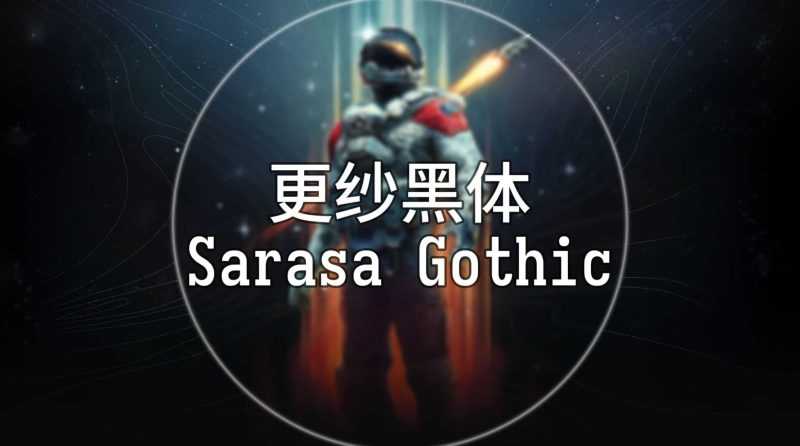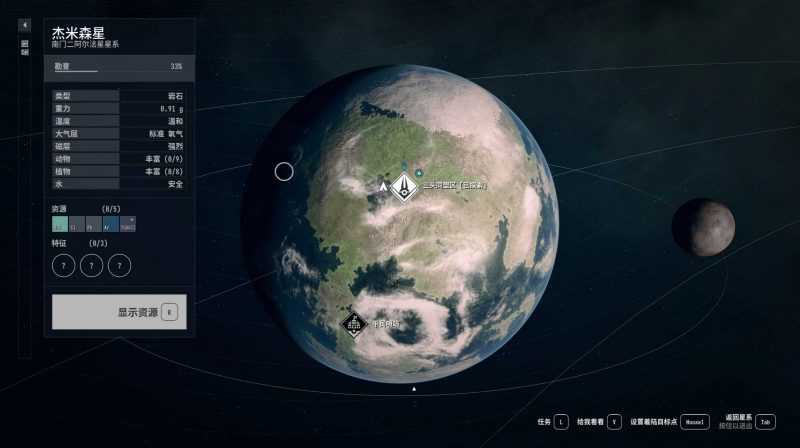
Лучший китайский шрифт — Sarasa Gothic
Особенности мода:
Замените китайский и английский шрифты игры по умолчанию шрифтом с открытым исходным кодом Sarasa Gothic / шрифт без засечек с более жирным шрифтом, который имеет более чистый внешний вид и лучшую разборчивость. Сделайте так, чтобы он выглядел чище и его было легче читать.
*0, 1 в количестве и размере O английских субтитров, регистр I и регистр L лучше различаются